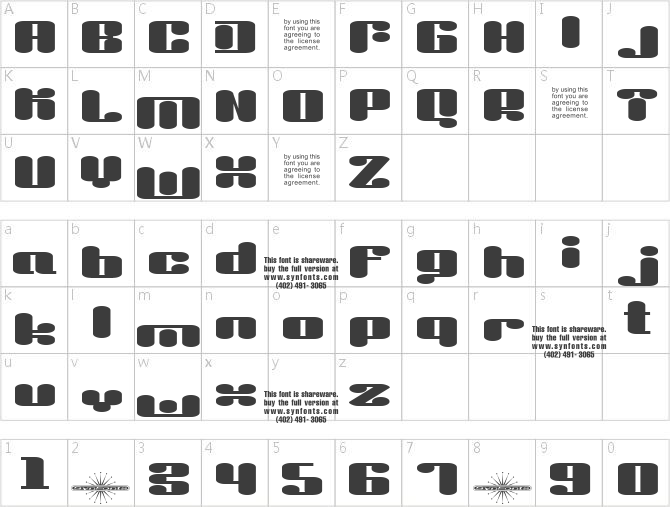
Liquid-Sex-UNPAID-DEMO 詳情頁
Liquid-Sex-UNPAID-DEMO字體字庫是一款讓人賞心悅目、百看不厭的英文字體,適合各類廣告和產(chǎn)品包裝設(shè)計(jì)應(yīng)用,字體大小0.03MB,格式為ttf字體,上傳用戶是sunlight,作者/版權(quán)方為未知